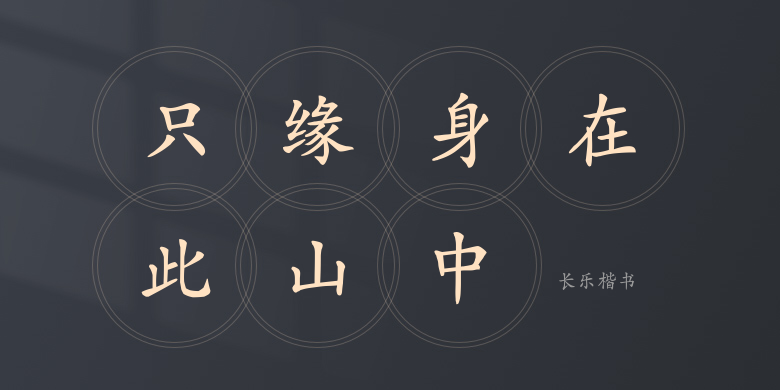
长乐楷书
长乐楷书,这款字体结构工整、笔画清晰,兼顾美观与易读性,适用于标题、正文、海报、包装、LOGO 等多种场景。字形优雅稳定,风格百搭耐看,适配日常排版与创意设计,让文字呈现更舒适、更具质感。长乐楷书一笔一画,皆是细节,以均衡的比例、流畅的线条打造舒适视觉体验,字形端正大气,风格简约现代。无论是商业设计、品牌宣传还是日常排版,都能轻松驾驭,让文字更有格调与力量。长乐楷书字体下载。